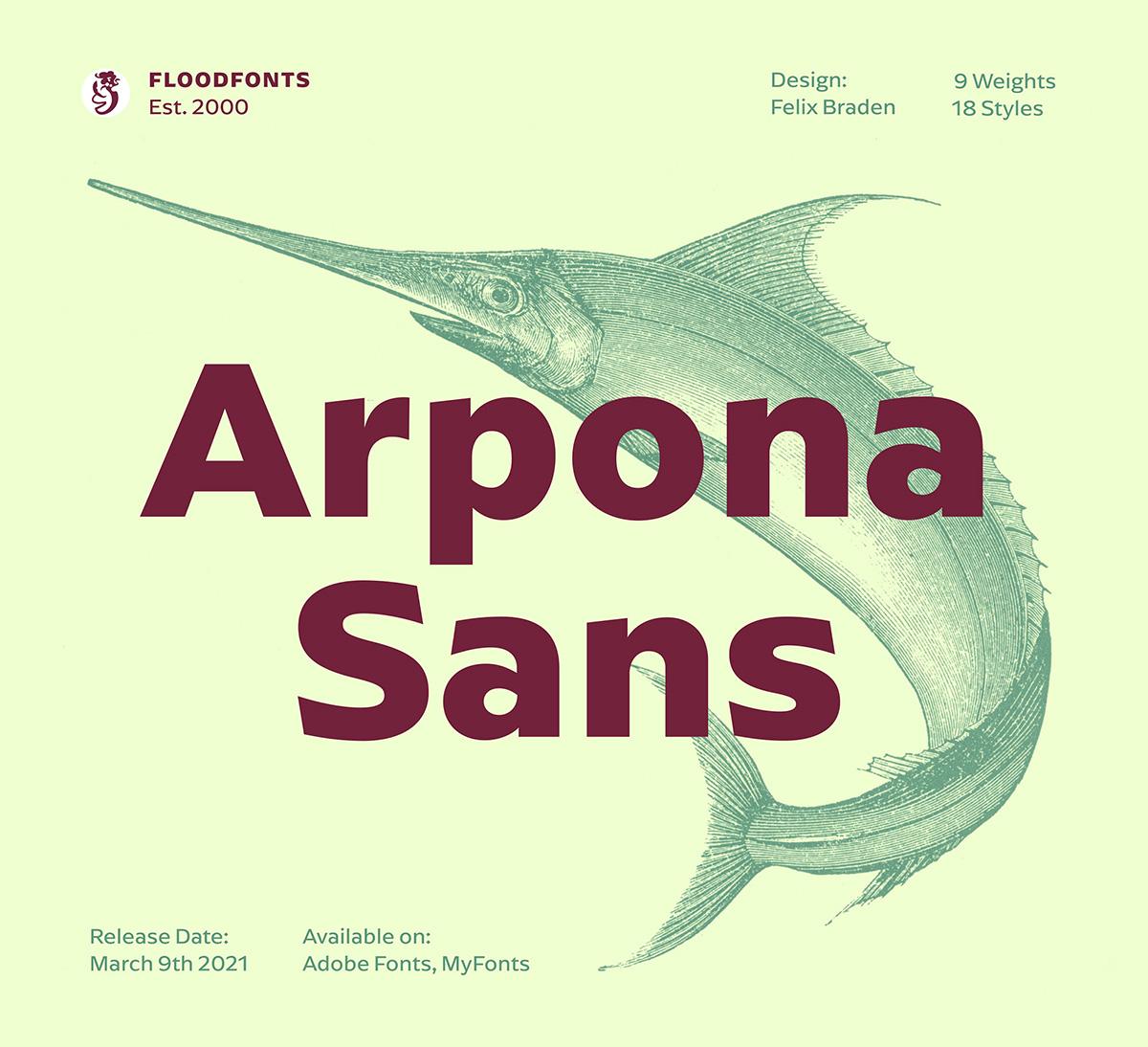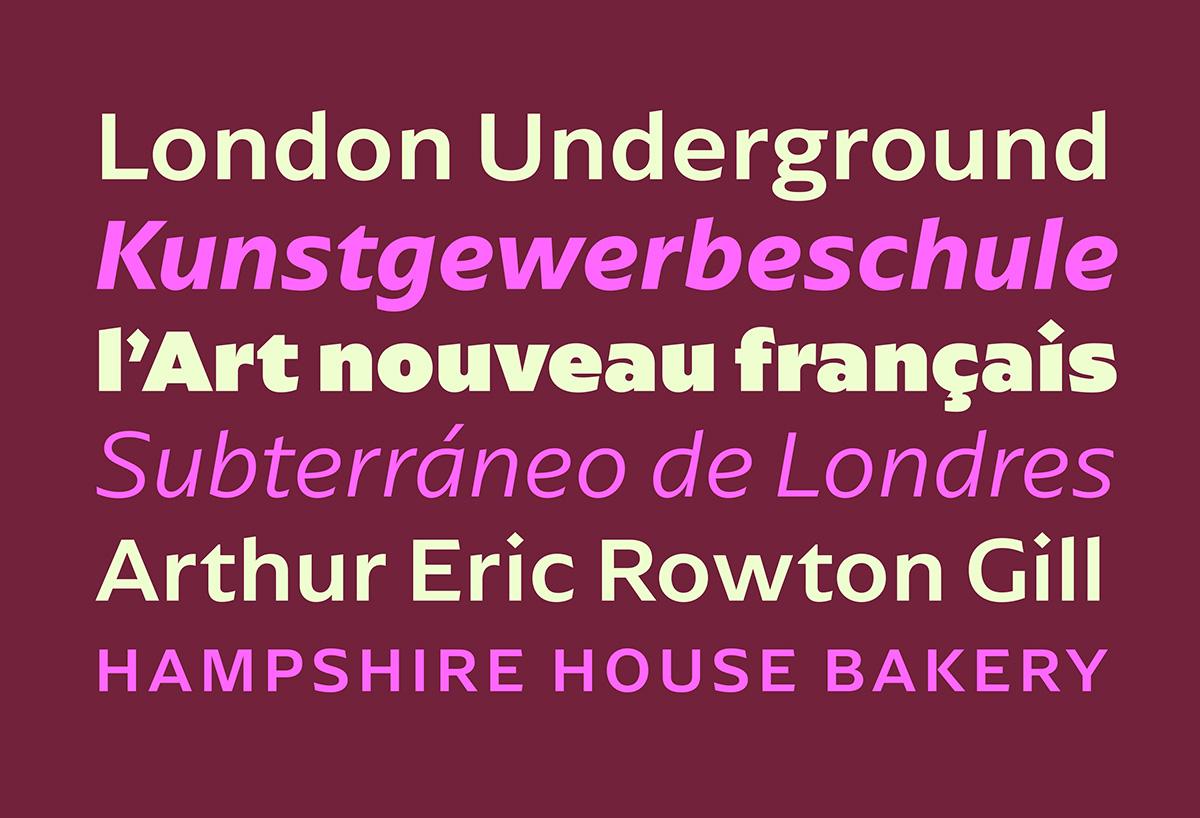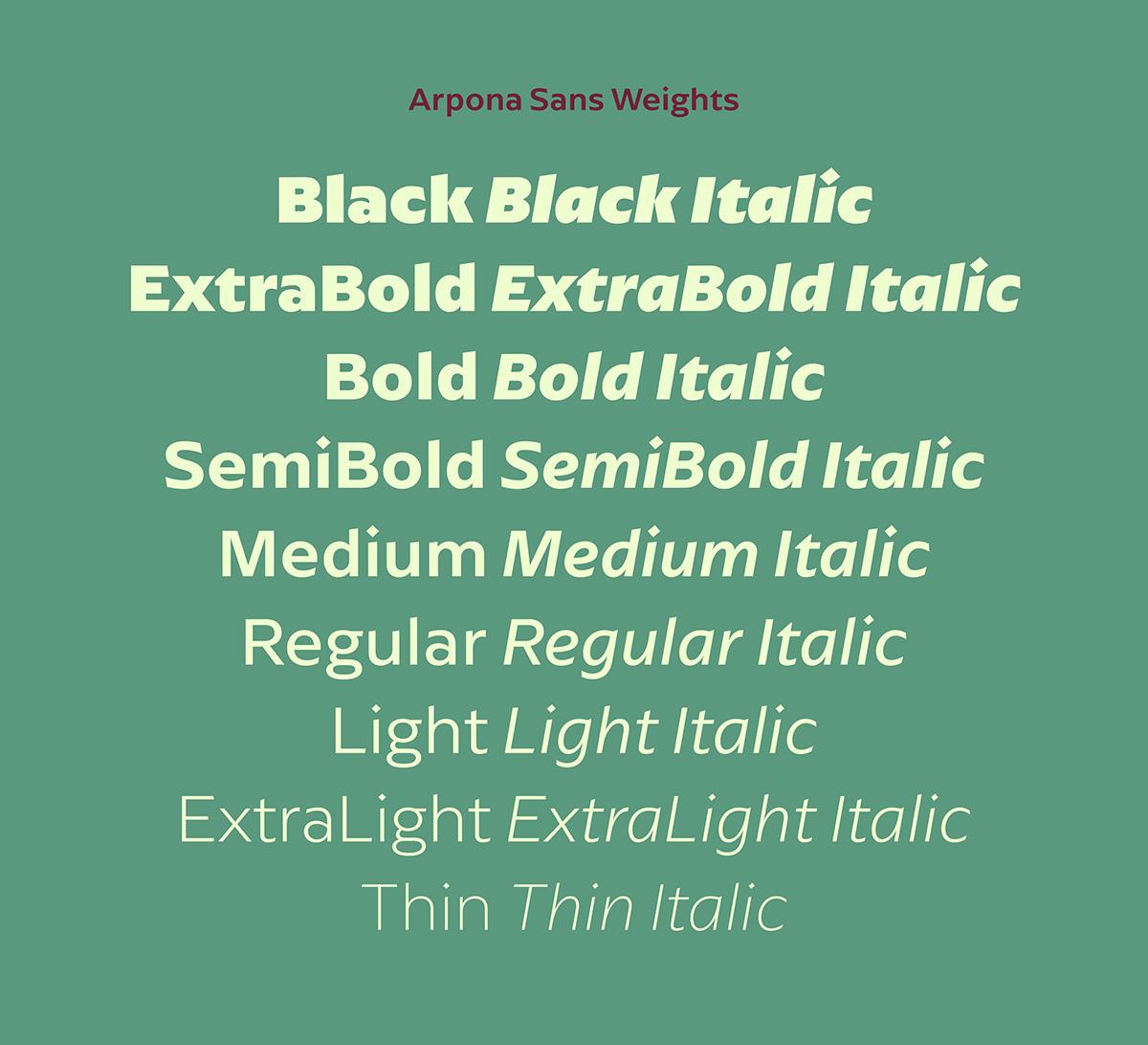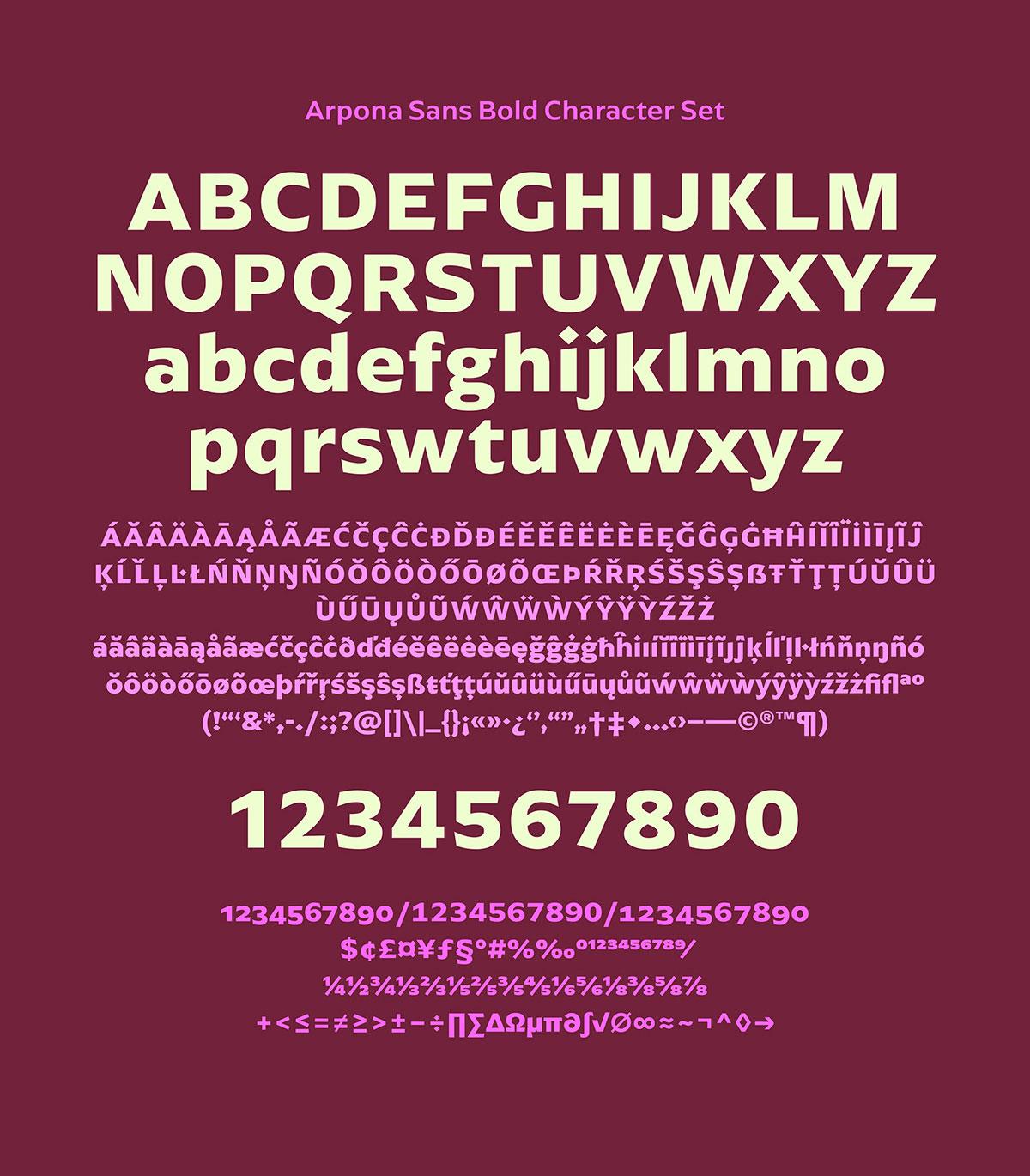
Neue Schriftfamilie Arpona Sans
Arpona Sans ist eine zeitgenössische Serifenlose, inspiriert von Edward Johnstons Schriftentwürfen für das Leitsystem der Londoner U-Bahn. Wie auch ihr serifenbetontes Pendant "Arpona" ist sie eine Symbiose aus verschiedenen Designkonzepten. Arpona Sans verbindet die Ästhetik einer geometrischen Sans mit der guten Lesbarkeit durch das humanistische Konzept und der Sachlichkeit der klassizistischen Proportionen.
Die Familie hat neun Schnitte, von Thin bis Black, sowie entsprechende Kursiven. Jeder Stil umfasst 588 Glyphen, die alle west-, ost- und mitteleuropäischen Sprachen unterstützen, darunter vier Ziffernsätze und verschiedene Währungssymbole.
Foundry: Floodfonts
Designer: Felix Braden
Schnitte: 18, Thin bis Black (inkl. Italics)
alle west-, ost- und mitteleuropäischen Sprachen unterstützen
Ich möchte nur mild klugscheißen, aber Du wolltest sicherlich sagen, dass die europäischen Sprachen unterstützt werden, die das lateinische Alphabet als Basis haben. In Ost- und Mitteleuropä werden mindestens kyrillische Glyphen genutzt.